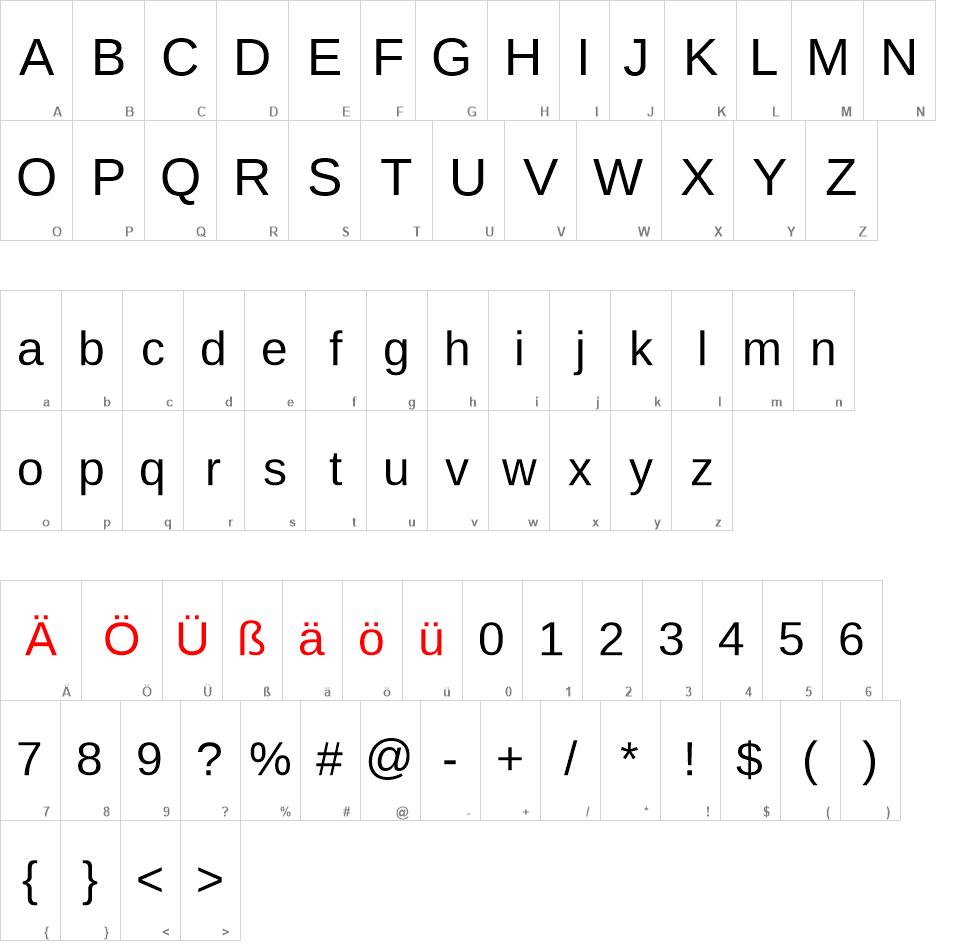
Arimo - Helvetica
Arimo - Helvetica font
Helvetica ist die am häufigsten verwendete Schriftart.
Die Schriftart Arimo ähnelt der Schriftart helvetica.
Es wurde behauptet, dass es von der Schriftart Helvetian in der Schriftart Arial abgeleitet wurde. An vielen Stellen hieß es, dass der Helvetica-Font von Microsoft gekauft wurde und dass einige Buchstaben als Arial mit einem 45-Grad-Winkel dargestellt wurden.
Arimo wird von Google auf der Schriftart unterstützt und ähnelt der Helvetica-Schriftart mehr als Arial-Schriftart. Arimo ist den ersten drei Buchstaben des Wortes Arial ähnlich.
Die Schriftart Helvetica gehört zu den 5 meistverkauften Schriften jedes Jahr.
Benutzer, die die Schriftart Helvetica mögen, können die kostenlose Schriftart arimo font kostenlos mit 4 font options benutzen. Arimo Schriftart ist moderner als Helvetica.
Es ist eine Schriftart, die Sie in Ihrer Unternehmensarbeit wie Katalog bevorzugen können. Sie können Katalogschriftart sagen.